가변폰트에 대한 통념 4가지, 지금도 맞는 말일까
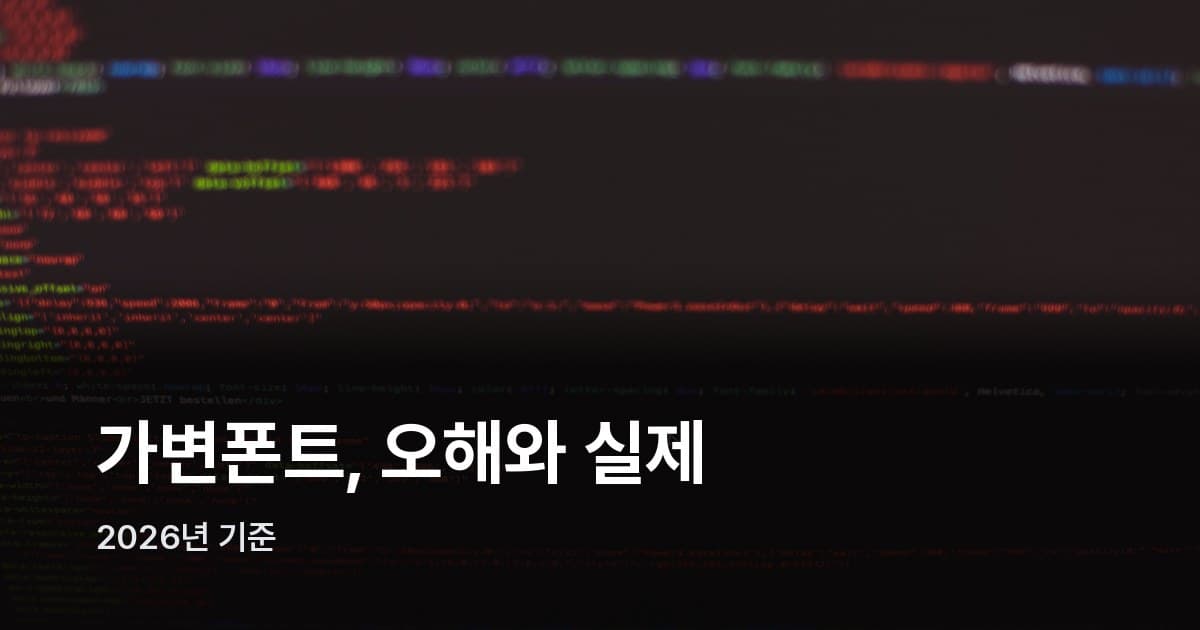
"가변폰트요? 파일 무겁고 설정 복잡하다던데, 실무에선 잘 안 쓰지 않나요?"
처음 가변폰트를 알게 됐을 때 이런 말을 들었다. 반박할 말도 딱히 없어서 그냥 넘어갔는데, 나중에 Pretendard Variable 관련 자료를 파고들면서 생각이 달라졌다. 저 말들이 틀린 건 아닌데, 2019년 기준으로 맞는 말이었다는 걸 알게 됐거든요.
가변폰트를 둘러싼 통념은 생각보다 오래된 이야기에 기대고 있는 경우가 많다. 브라우저 지원도, 한글 폰트 생태계도, 실제 파일 크기 조건도 그사이 꽤 많이 바뀌었다. 네 가지 통념을 하나씩 짚어보자.
"파일이 더 무겁다"는 말, 비교 기준이 잘못됐다
가변폰트 파일 하나를 처음 열면 800KB 넘는 숫자가 나오니까 "무겁다"는 인상을 받기 쉽다. 그런데 그 비교가 공평하지 않다는 게 문제다.
실무에서 웹폰트를 쓸 때 단일 weight만 쓰는 경우는 드물다. 보통 Regular, SemiBold, Bold 최소 세 개는 함께 로드한다. 정적 폰트는 weight 수만큼 파일이 필요하고, 각각 HTTP 요청이 따로 나간다. 가변폰트는 그 전체 range가 파일 하나에 들어 있다.
Pretendard로 직접 비교하면 이렇다.
| 방식 | 파일 수 | 합산 용량 (woff2 기준) |
|---|---|---|
| Pretendard 정적 3개 (Regular·SemiBold·Bold) | 3개 | 약 270~300KB |
| PretendardVariable.woff2 원본 | 1개 | 약 2.0MB |
| PretendardVariable 서브셋 최적화 후 | 1개 | 약 273KB |
서브셋 없이 원본 그대로 쓰면 확실히 무겁다. 하지만 자주 쓰는 한글 글리프와 weight 범위만 추려서 서브셋 처리하면 273KB 수준으로 내려간다. 원본 2.0MB 대비 약 86% 감소한 셈이다. 정적 3개 파일 합산과 거의 같은 용량이면서 HTTP 요청은 세 배 줄어드는 셈이다.
서브셋 최적화란 간단히 말하면 폰트 파일에서 실제로 쓸 글자와 weight 범위만 골라 다시 패키징하는 작업이다. 11,172자 전체가 아니라 자주 쓰는 한글 2,350자 남짓과 숫자·영문 기본셋만 남기면 파일 크기가 극적으로 줄어든다. 기존 정적 폰트 방식에서는 weight별로 이 작업을 여러 번 해야 했지만, 가변폰트는 파일 하나로 끝난다는 게 차이다.
"가변폰트가 무겁다"는 말은 서브셋 최적화 없이 단순 비교했을 때 나오는 결론이다. 최적화 후 실무 조건에서 비교하면 이야기가 달라진다.
"브라우저 지원이 불안정하다"는 건 2019년 얘기다
가변폰트가 처음 등장하던 시기에 이 말은 사실이었다. 브라우저마다 지원 범위가 제각각이었고, 모바일은 더 불안정했다.
지금은 다르다. Can I Use 기준 전 세계 브라우저의 96% 이상이 가변폰트를 지원한다. Chrome, Edge, Firefox, Safari, Samsung Internet, Opera, iOS Safari까지 모두 정식 지원이다. 지원하지 않는 환경은 사실상 구형 Internet Explorer뿐이다.
실질적으로 어떤 의미냐면 — 오늘날 웹 서비스의 주류 브라우저는 전부 가변폰트를 쓸 수 있다는 얘기다. Chrome과 Firefox는 2018년, Safari는 2018년 macOS Mojave 기준, Edge는 2019년 초부터 정식 지원에 들어왔다. 이미 6~7년이 지난 얘기다.
@font-face에 format('woff2-variations')를 명시하면 지원 브라우저에선 가변폰트를, 나머지에선 일반 format('woff2')로 폴백 처리할 수 있어서 하위 호환도 깔끔하게 된다. 브라우저 지원이 걱정돼서 가변폰트를 못 쓰겠다면, 그 걱정의 근거가 언제 것인지 먼저 확인해봐야 한다.
"CSS 설정이 복잡하다"는 건 낯선 이름에 겁먹은 것이다
font-variation-settings라는 속성 이름을 처음 보면 뭔가 복잡한 게 있을 것 같다는 느낌이 드는데, 실제로 열어보면 기존 @font-face 선언에서 딱 두 줄이 달라질 뿐이다.
가장 많이 쓰이는 패턴은 이렇다.
@font-face {
font-family: 'PretendardVariable';
src: url('PretendardVariable.woff2') format('woff2-variations');
font-weight: 100 900;
font-style: normal;
font-display: swap;
}
body {
font-family: 'PretendardVariable', sans-serif;
font-weight: 400;
}
h1 {
font-weight: 700;
}
font-weight: 100 900으로 가변 범위를 한 번 선언해두면, 이후엔 평소처럼 font-weight: 400 이런 식으로 쓰면 된다. 브라우저가 내부적으로 wght 축과 font-weight 값을 매핑해서 처리하기 때문에, 가변폰트를 쓴다고 해서 기존 CSS 작성 방식을 바꿀 필요가 없다. 이미 쓰던 font-weight 숫자를 그대로 유지하면 된다.
더 세밀하게 제어하고 싶을 때는 font-variation-settings를 쓴다. 폰트 디자이너가 정의한 변형 가능한 축인데, 대표적으로 세 가지가 자주 쓰인다. wght는 굵기 축으로 100~900 사이 어떤 값이든 정확하게 표현하고, slnt는 기울기를 이탤릭처럼 이분법이 아니라 연속값으로 조절해 미묘한 경사를 표현할 수 있다. wdth는 글자의 가로 폭 비율을 조절하는 축으로, 좁거나 넓은 변형 서체를 별도 파일 없이 구현할 수 있다.
.display-text {
font-variation-settings: 'wght' 650, 'slnt' -5;
}
정적 폰트에서는 SemiBold(600)와 Bold(700) 사이에 값을 줄 방법이 없다. 가변폰트에서는 650 같은 중간값도 정확하게 표현된다. 이 유연함이 가변폰트를 쓰는 이유의 절반이다.
"한글 가변폰트는 아직 없다"는 통념, 실무 선택지가 이미 넷이다
"한글은 글자 수가 너무 많아서 가변폰트 만들기 어렵다"는 말 자체는 사실이다. 현대 한글 11,172자를 전부 담아 가변 처리하려면 만만치 않은 작업이 필요하다. 이 어려움이 "아직 없다"는 오해로 굳어진 것이다.
틀렸다. 실무에서 당장 쓸 수 있는 한글 가변폰트가 이미 여럿 나와 있다.
가장 먼저 손이 가는 건 역시 Pretendard Variable이다. OFL 라이선스라 상업 사용도 가능하고, GitHub 공식 저장소에서 바로 받을 수 있다. 디자인 시스템을 구축하는 팀에서 많이 선택하는 이유가 여기 있다. weight 범위(Thin 100 ~ Black 900)가 넓고 라이선스 걱정이 없으니 한 번 설정해두면 두고두고 쓸 수 있다.
Noto Sans KR Variable은 구글 폰트에서 CDN 방식으로 제공해, 별도 다운로드 없이 <link> 한 줄이면 바로 임베드할 수 있다. 사이드 프로젝트나 빠르게 세팅해야 하는 경우에 편하다. 나눔스퀘어 네오 Variable은 네이버와 산돌이 협업한 폰트로, 현대 한글 11,172자 완성형을 전부 담아 특수한 글자가 깨질 걱정이 없다는 게 강점이다. 세리프 계열이 필요하다면 구글 폰트에 올라온 한글 세리프 가변폰트 Hahmlet도 선택지다.
"없다"는 통념이 아직 도는 건, 2020년 이전 한글 가변폰트 생태계가 실제로 빈약했기 때문이다. 지금은 아니다. Pretendard Variable의 웹사이트 적용 가능 여부와 OFL 조건 상세는 폰트비에서 확인할 수 있다.
그럼 "막연한 인상"이 왜 이렇게 오래 살아남았나
네 가지 통념이 지금도 도는 데에는 공통된 패턴이 있다. 초기 사실이 맞았다는 것이다. 2018~2020년 가변폰트는 실제로 브라우저 지원이 불안정했고, 한글 가변폰트는 없다시피 했고, 서브셋 최적화 없이 쓰면 분명히 무거웠다. 그 인상이 검증 없이 굳었다.
하지만 가변폰트가 항상 유리한 건 아니라는 점은 지금도 사실이다. 사이트에서 딱 하나의 weight만 쓰고 서브셋 최적화까지 할 여력이 없다면, 서브셋 정적 woff2 파일 하나가 오히려 더 가벼울 수 있다. 통념을 깨는 게 목표가 아니라 실제 상황에 맞는 선택을 하는 게 목표다.
weight를 3개 이상 쓰거나 미세한 굵기 조절이 필요한 디자인 시스템이라면 가변폰트 쪽이 분명히 이득이다. 특히 랜딩 페이지처럼 헤딩·본문·강조 텍스트가 각자 다른 굵기를 쓰는 구조라면, 가변폰트 하나로 정리하는 게 유지보수 면에서도 편하다. 반대로 블로그처럼 본문 폰트 하나만 쓰고 서브셋 최적화에 손을 댈 여력이 없다면 정적 woff2로도 충분하다.
막연하게 "무겁고 복잡하다"는 인상으로 지나치기보다, 실제로 몇 개 weight를 로드하는지부터 세어보는 게 시작이다. Pretendard Variable이라면 @font-face 한 줄 선언해보고 실제 파일 크기를 재보는 것만으로도 감이 온다. 서브셋 최적화 여부는 그 다음에 판단해도 충분히 늦지 않다. 통념을 버리는 데 드는 비용은 그 정도면 충분하다 🙂